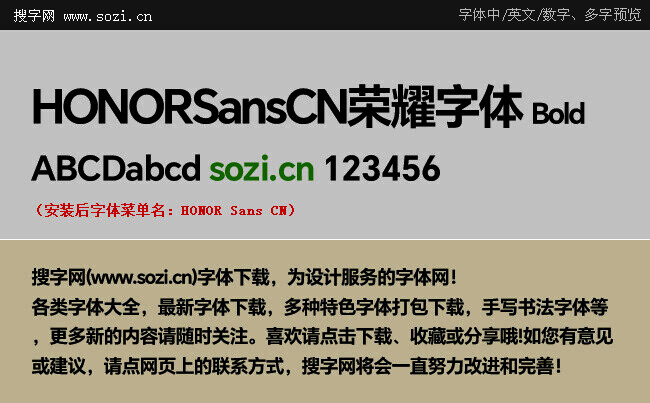
HONORSansCN榮耀字體Bold
搜字網(wǎng)給大家提供一款HONORSansCN榮耀字體Bold中文字體下載,榮耀字體HONOR Sans是由榮耀MagicOS聯(lián)手方正帶來的一套全新的免費(fèi)可商用中文字體,包含了 9 種字重,HONOR Sans擁有簡潔生動的筆劃以及平滑優(yōu)美的曲線,相比標(biāo)準(zhǔn)的黑體則在筆畫的曲率、結(jié)構(gòu)布局上進(jìn)行了優(yōu)化,很好地提升了可讀性以及文字辨識度,讓排版更加舒服,看起來也更加優(yōu)雅,能有效降低長時間閱讀時對視覺造成的疲勞。 適用于標(biāo)題設(shè)計(jì)、海報(bào)設(shè)計(jì)、書籍排版以及網(wǎng)頁設(shè)計(jì)等應(yīng)用。